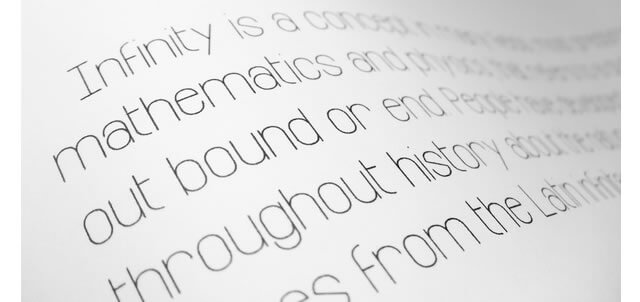
美しい!ヘッドラインやタイトルに最適なフリーフォント60選
ここでは、デザイナーが常に求めているユニークかつ読みやすいフリーフォント、 美しい見出しとタイトルのためのフォントに焦点を当てています。 これらのフォントをウェブ上や印刷物上で使用するかどうかに関わらず、フォントには読者またはユーザにプロフェッショナルなインパクトを与える必要があります。
ALEO
Buffalo
Mathematical
New York Font
Langdon
Bw Glenn Sans
Hapna Mono
Befitting Script
Muchacho
Brightshine Typeface
Calendas Plus
Pathways
Mission Gothic
Humblle
Lovelo
Bw Quinta
Varela
Foundry
Musket
Frank
Bariol Regular
Cheddar Gothic
Fénix
Sevastian
Mecca
Bw Surco
Municipal
Fibre
Twentytwelve Slab
Breymont
Promesh
Kreon
Vim SM
Biko
Knubi
Tale
Palo Alto
Kelson Sans